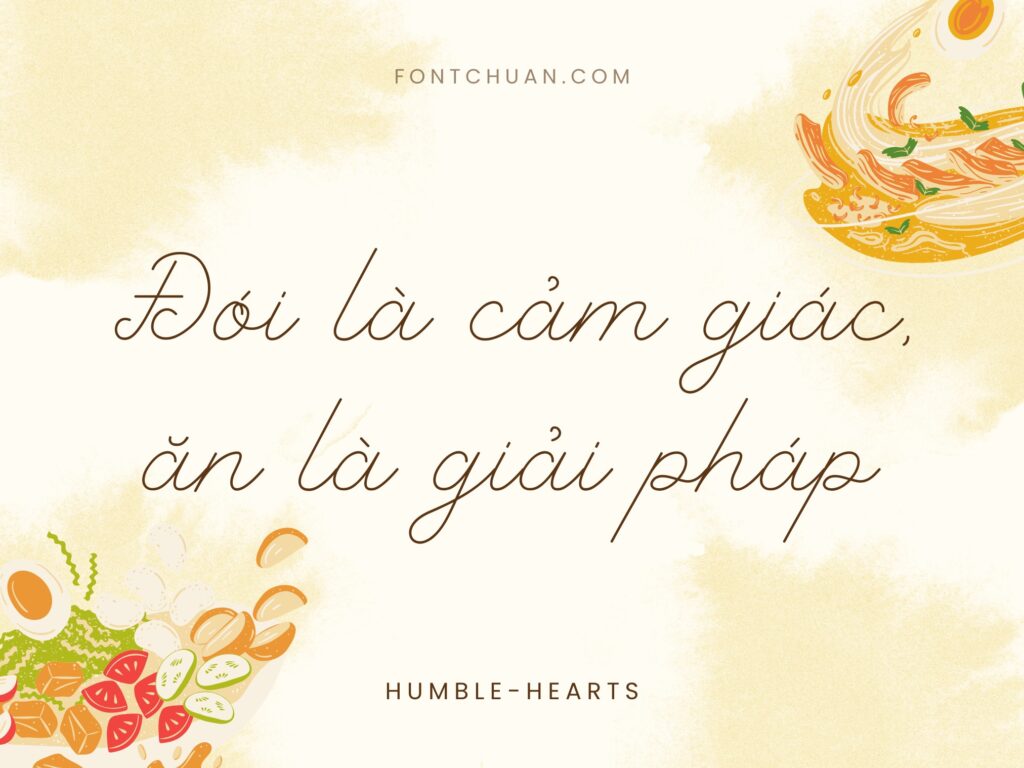
Font iCiel Humble Hearts Việt Hóa
Tác giả Font: Joanne Hewitt
Humble Hearts là một font chữ script đơn nét được thiết kế bởi Joanne Hewitt, mang phong cách viết tay độc đáo và cá tính. Với hơn 700 ký tự, Humble Hearts cung cấp sự linh hoạt cho các nhà thiết kế trong việc tạo ra các logo, thiệp mời, poster và nhiều sản phẩm sáng tạo khác. Đặc biệt, font này đã được Việt hóa bởi Iciel, hỗ trợ tiếng Việt cùng nhiều ngôn ngữ khác, đáp ứng nhu cầu đa dạng của người dùng. Thành viên của Font Chuẩn đã sưu tầm và chia sẻ font này, giúp cộng đồng thiết kế ứng dụng dễ dàng trong các dự án của mình.
Về đặc điểm thiết kế, Humble Hearts sở hữu các đường nét mềm mại, liền mạch, tạo cảm giác thân thiện và ấm áp. Font này phù hợp cho các thiết kế như thiệp mời, logo, bao bì sản phẩm và các ấn phẩm truyền thông xã hội. Ngoài ra, Humble Hearts còn thích hợp cho các ngành nghề như quảng cáo, ẩm thực, thiệp cưới và spa, cùng các sự kiện đặc biệt như lễ hội, sinh nhật, Valentine và Trung thu.